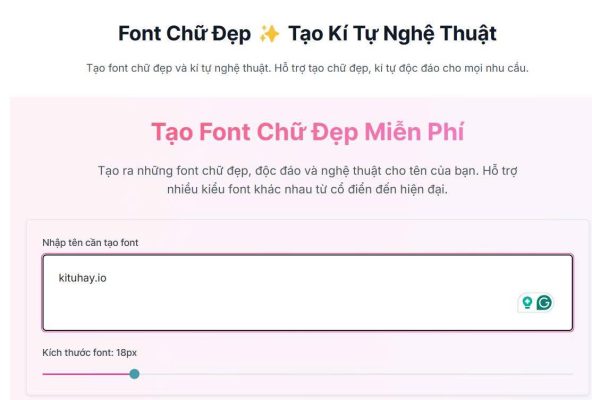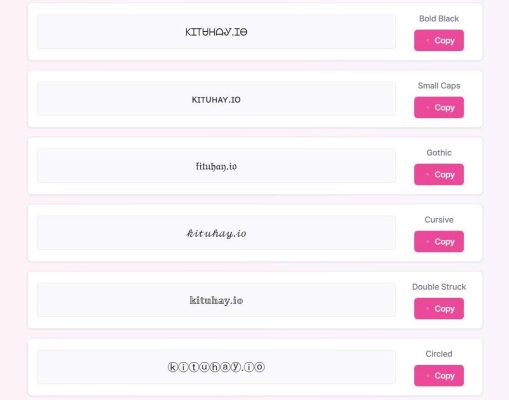
Font chữ đẹp trendy để bạn “hô biến” chữ thường thành chất riêng
Bạn đang loay hoay đặt tên game cho ngầu? Viết bio TikTok hoài mà vẫn thấy “thiếu muối”? Hay chỉ đơn giản là muốn story của mình có điểm nhấn hơn đứa bạn thân? Vậy thì đã đến lúc bạn cần đến font chữ đẹp – “vũ khí” bí mật giúp mọi dòng chữ trở nên nổi bật, cá tính và đậm chất riêng.
Cùng tìm hiểu ngay top font chữ đẹp và chất như nước cất để tạo dấu ấn riêng biệt – từ Facebook, Tiktok cho tới thiết kế website, poster nhé.
Font chữ đẹp là những kiểu chữ được thiết kế đặc biệt để trông ấn tượng, độc đáo, hoặc nghệ thuật hơn so với font mặc định thông thường. Ví dụ như:
• Chữ in đậm / in nghiêng / gạch chân
• Chữ cách điệu với ký tự lạ (𝓵𝓸𝓿𝓮, Ⓑⓤⓑⓑⓛⓔ, 𝕯𝖆𝖗𝖐𝖓𝖊𝖘𝖘)
• Chữ cách khoảng, lộn ngược, viết kiểu hacker
• Chữ kết hợp icon hoặc emoji
Bạn có thể bắt gặp font chữ đẹp ở:
• Tên nhân vật trong game như Free Fire, Liên Quân, PUBG,…
• Bio TikTok, story Facebook, caption Instagram
• Trên các video viral YouTube Shorts, Reels,…
Hướng dẫn tạo font chữ đẹp online đơn giản nhất
Bạn không cần cài app rắc rối hay biết thiết kế gì cả. Chỉ cần vài bước cực đơn giản với công cụ tạo font chữ đẹp KiTuHay là đã có ngay font chữ đẹp để “biến hình” tên game, status mạng xã hội hay tiểu sử cá nhân.
KiTuHay là công cụ tạo kí tự đặc biệt, font chữ đẹp và nhiều tiện ích viết tên online hoàn toàn miễn phí. Giao diện đơn giản, dễ dùng, không cần đăng ký tài khoản, ai cũng có thể nhanh chóng tạo được những cái tên, dòng trạng thái hay chữ in đậm, in nghiêng độc đáo chỉ với vài cú click.
Cách tạo kiểu chữ đẹp trong vài giây mà không cần biết thiết kế:
ruy cập công cụ chuyển font online tại địa chỉ https://kituhay.io/font-chu-dep. Công cụ này tương thích với mọi thiết bị, từ máy tính đến điện thoại, từ Android đến IOS. Gõ tên, câu quote, hay status vào ô trắng sau đó tùy chỉnh kích thước font bằng cách kéo thanh công cụ Công cụ sẽ tự động hiển thị hàng chục kiểu font chữ đẹp, độc đáo và đầy cá tính. Bạn chỉ cần chọn font chữ bạn yêu thích. Nhấn Copy vào kiểu font bạn ưng ý → Dán vào TikTok, Facebook, Liên Quân, Zalo,… đều được hỗ trợ.